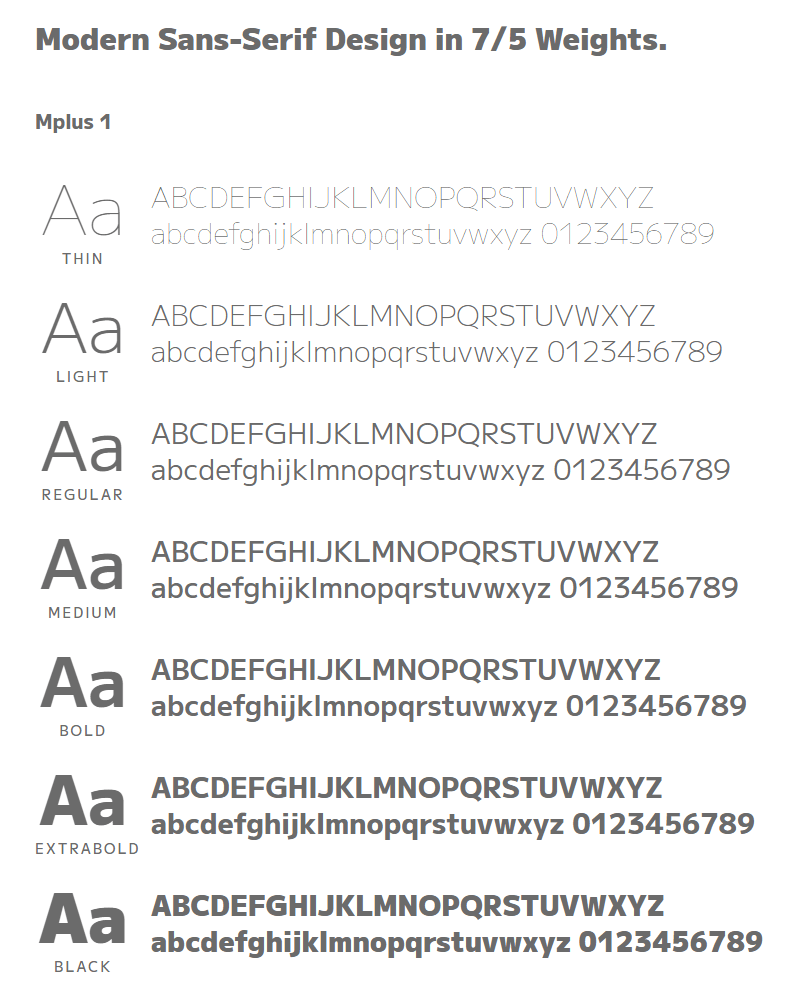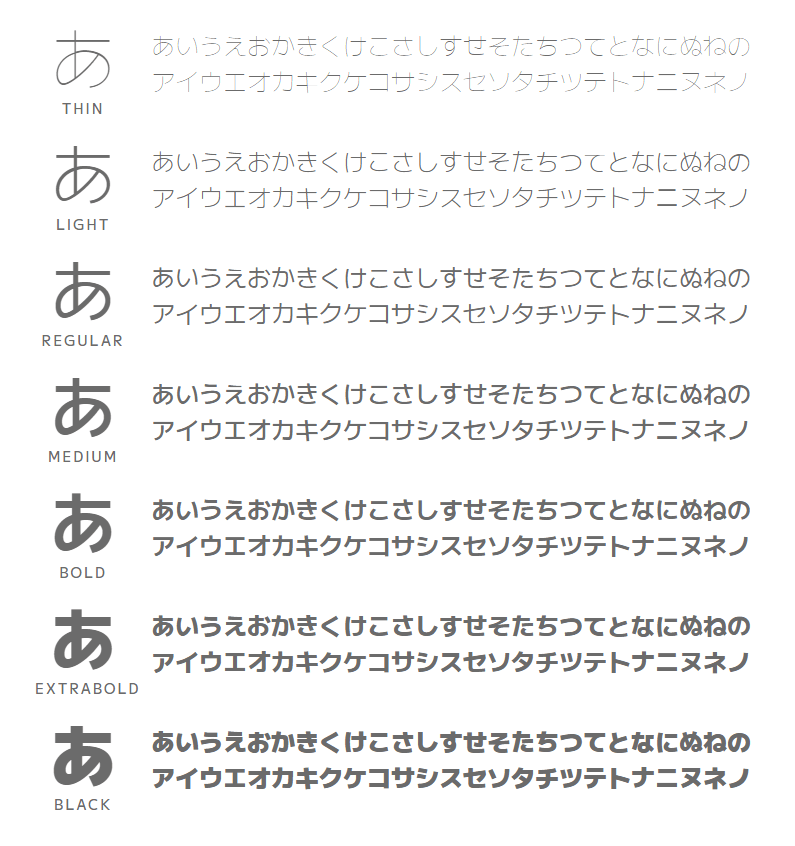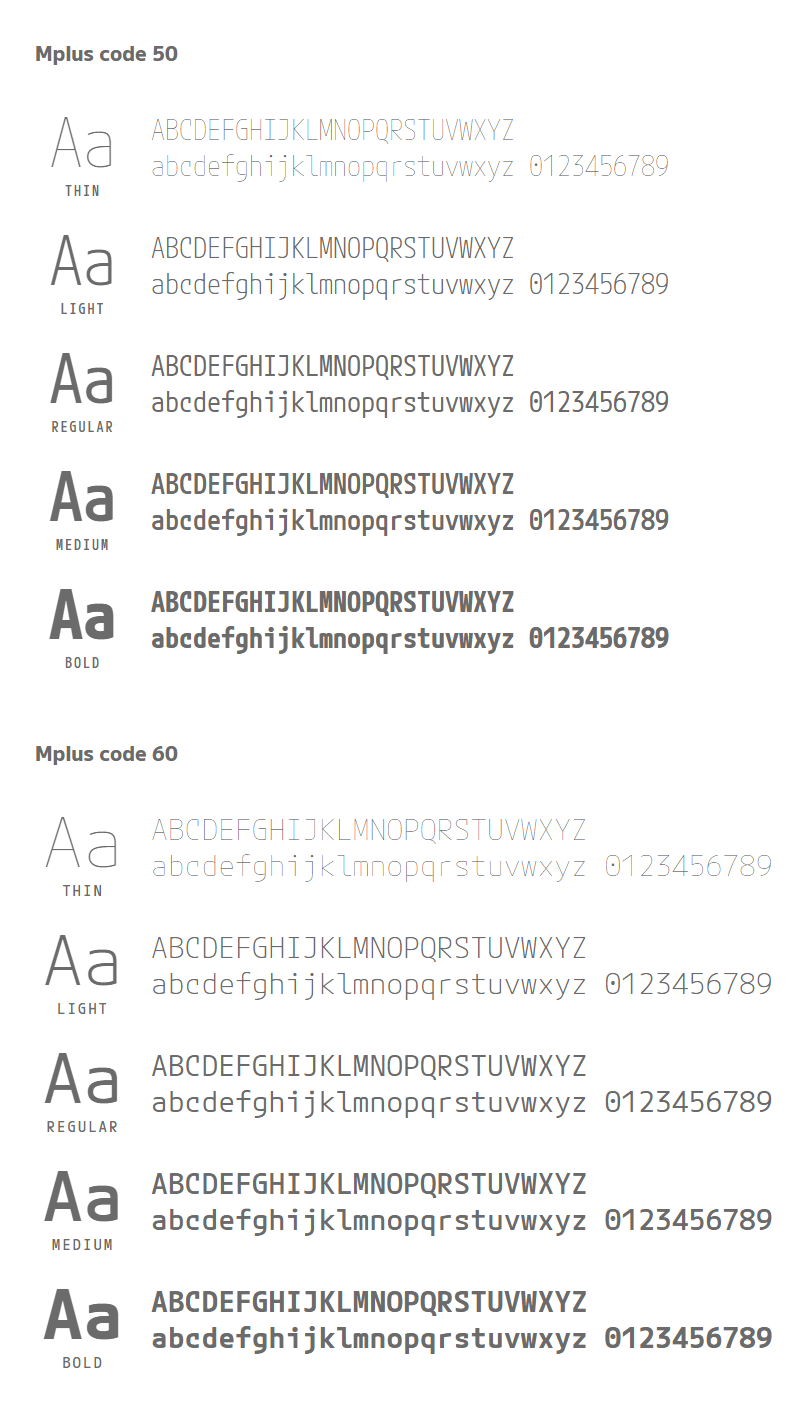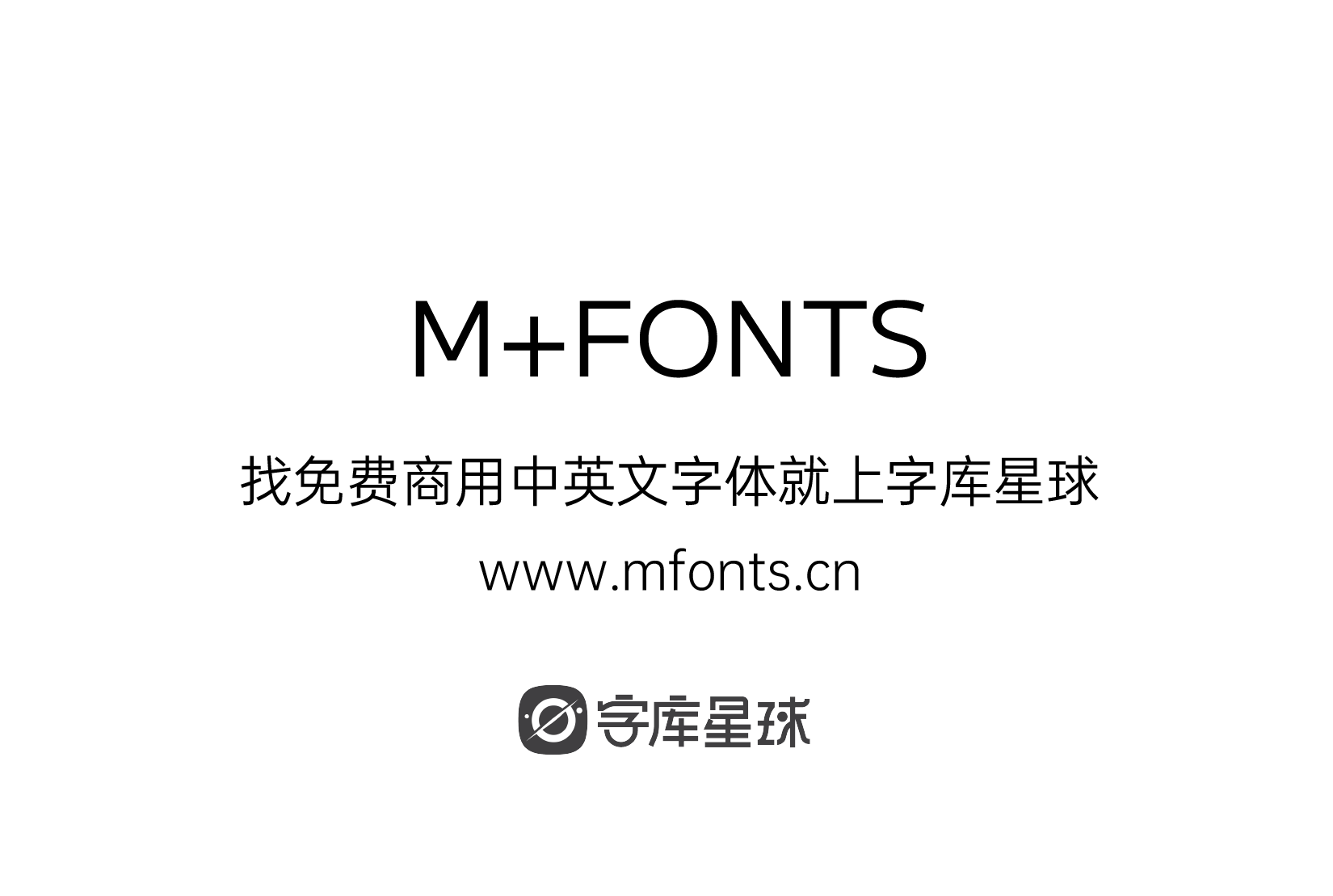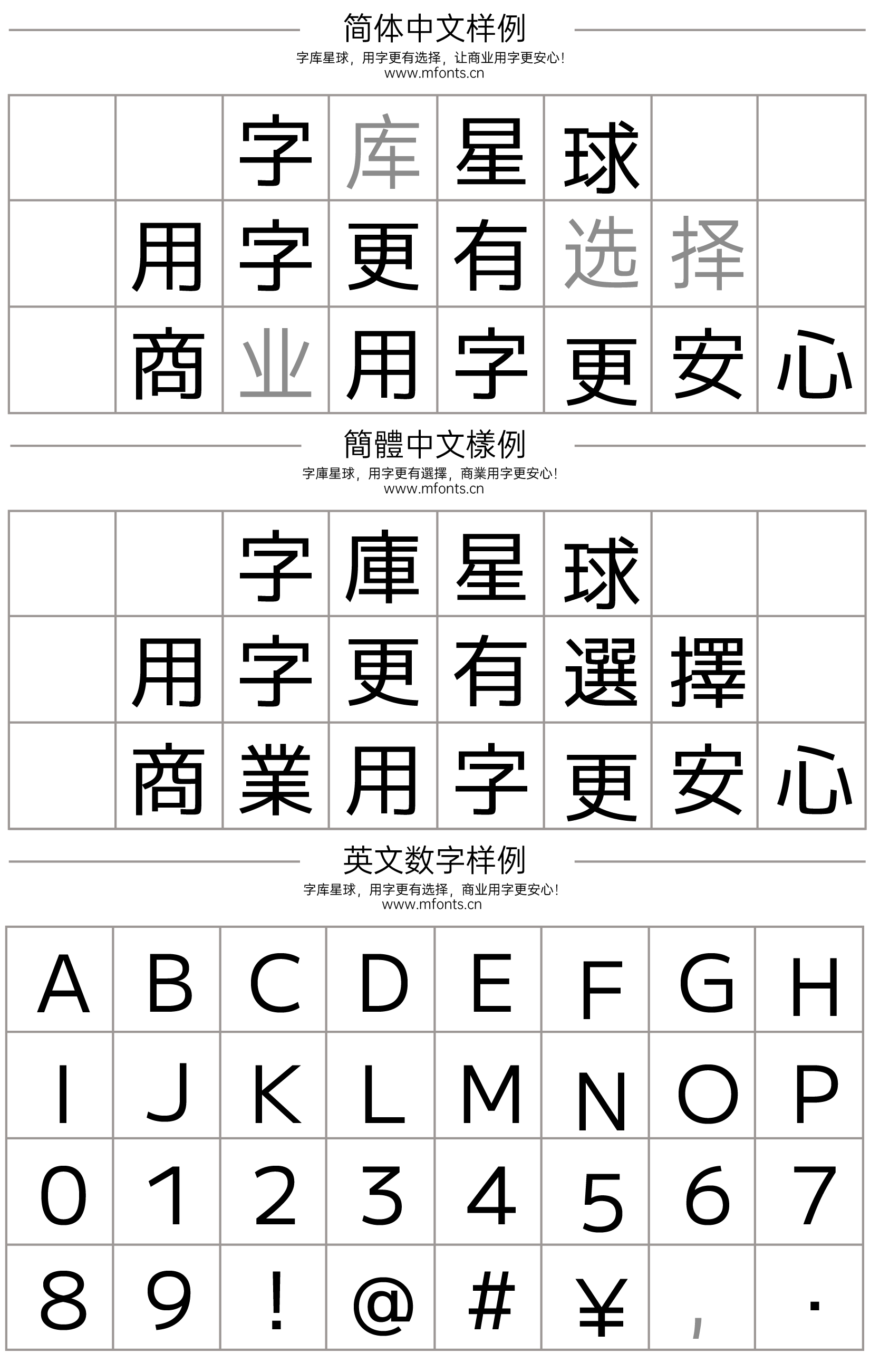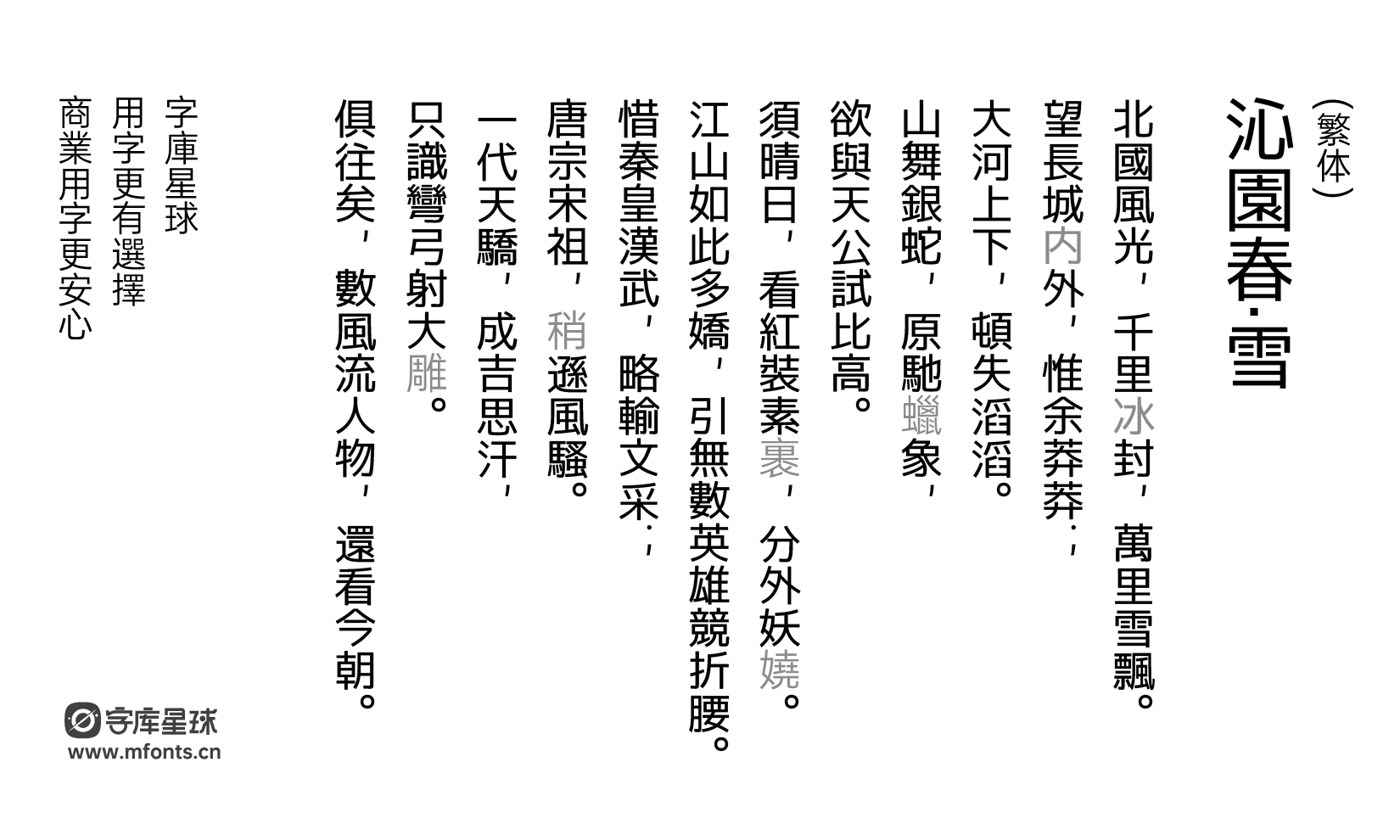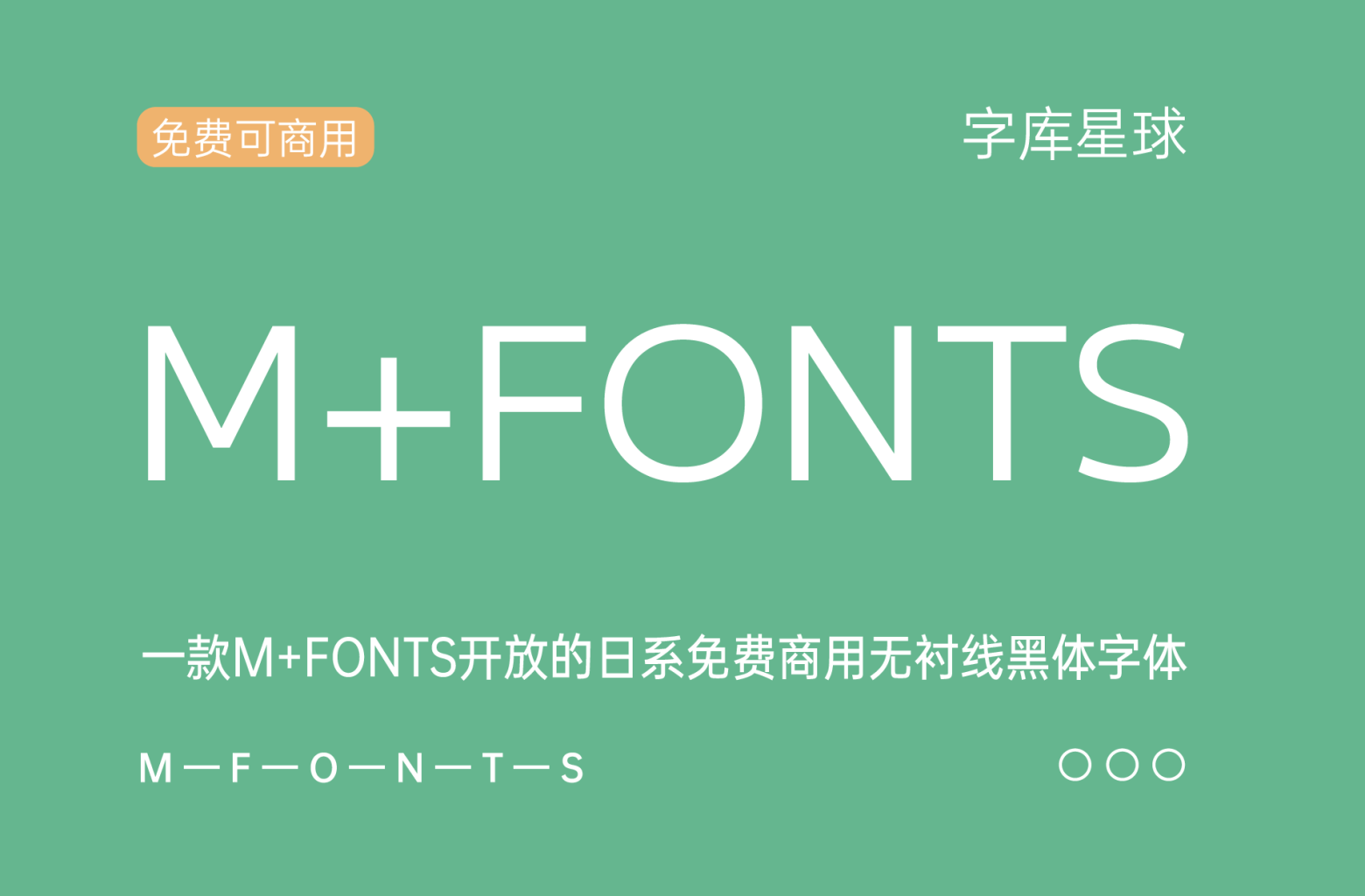
M+FONTS
M+FONTS发布于2003年,至今已经历18年。而今,M+FONTS发布M+2版本,并新增了可变字形,并把字体以OFL授权释出。
M PLUS 1/2 是无衬线字体,从细到黑有 9 个粗细,支持 GF Latin Plus 字形集,日语有 5700+ 个汉字。
Mplus1:舒适的曲线和直线的和谐,这种字体给人以现代而慷慨的印象,适合任何场合,包括小文本到大标题。
Mplus2:凭借有些经典的字体形式,这种字体追求经典现代的新标准。
在谷歌的支持下正在修改字体设计。现在,GF Latin Plus欧文文字组等文字组合了以前的汉字,Mplus1和Mplus2,并且Mplus code字体暂定公开中。新的文字设计也显示在现在看到的这个字体上。